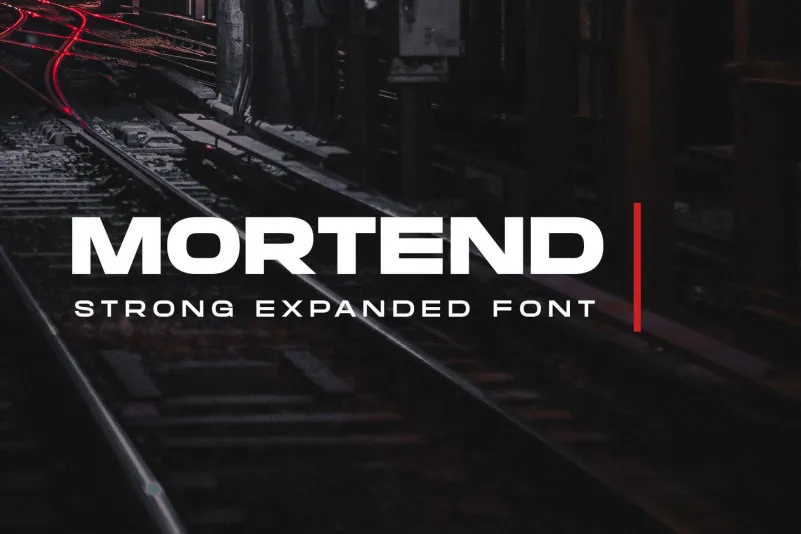
Morten Font é uma elegante fonte sans-serif que traz a essência do modernismo brutalista com uma pitada minimalista contemporânea. Inspirado nos posters dos anos 60 e na simplicidade de designs atuais, esta fonte masculina e robusta oferece um visual dinâmico para expressar sua criatividade. Com uma face forte e sofisticada que mantém a elegância, ela é perfeita para design gráfico, publicidade, sites pessoais e até mesmo materiais de apresentação. Morten Font é o seu companheiro ideal para criar mensagens modernas e impactantes sem perder sua personalidade única. Seja você um designer ou uma marca que busca adicionar um toque de sofisticação e ousadia a seus projetos, esta fonte tem tudo o que precisa.